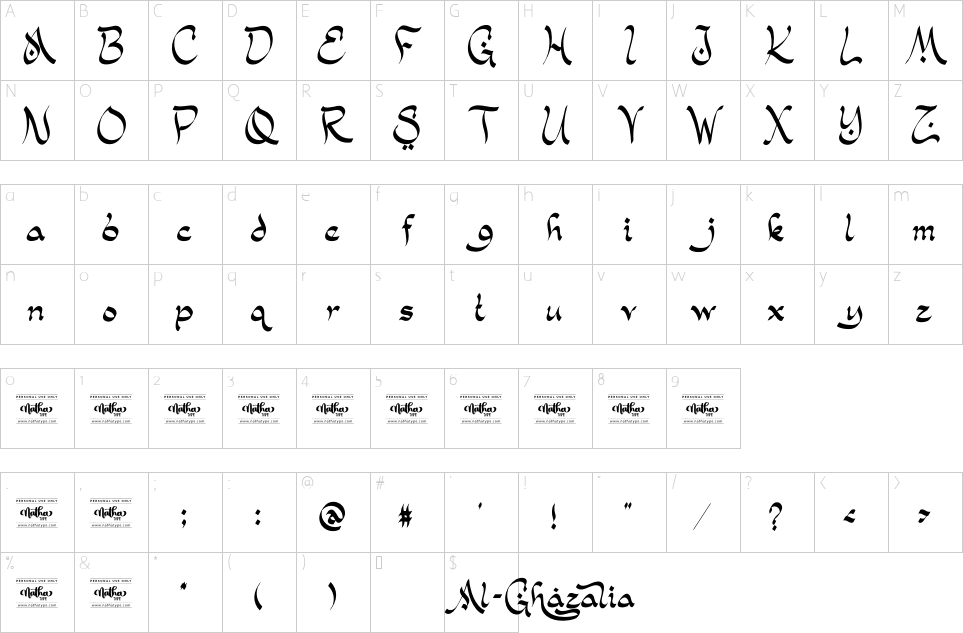
A fonte Al Ghazalia é uma escolha excelente para qualquer designer gráfico que busca uma fonte moderna e elegante. Desenhada pelo Dita Type, esta fonte é uma escolha adequada tanto para projetos de desenvolvimento pessoal quanto para iniciativas mais profissionais. Sua simplicidade e sofisticação a tornam uma opção popular entre os designers, que apreciam o equilíbrio entre legibilidade e estilo. Com seu design cuidadosamente pensado e sua simplicidade, Al Ghazalia é uma fonte gratuita e de qualidade para quem procura uma opção confiável e versátil para seus projetos. Al Ghazalia já foi baixada mais de 1.351 vezes, demonstrando seu valor e popularidade. Seja para criar design de logotipos, websites, materiais de marketing ou até mesmo design de documentos, Al Ghazalia oferece o acabamento perfeito para qualquer projeto.